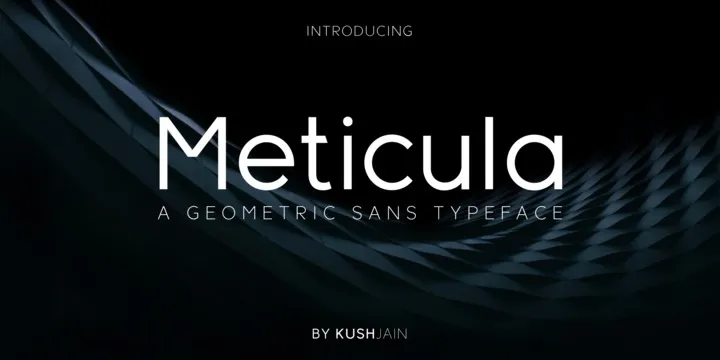
Meticula Font Family
A Meticula Font Family é uma famosa família de fontes sans-serif projetada pela 24Design, que vem com 18 diferentes tipos. Se você busca letras fortes, compostas por uma variedade de ligaturas únicas e estilos distintos, a Meticula é sua escolha perfeita. Uma fonte memorável, fashionável e elegante, essa família de letras atesta o rigoroso trabalho que 24Design investiu em desenvolvê-la com formas geométricas inspiradas em tipos modernos sans-serif. A famosa Meticula vem embalada com 8 versões estilizadas e um font in-line apresentando ganchos acentuados. Além disso, a família inclui uma tipografia itálica que complementa as formas rectângulares de sua versão estándar. Nossa introdução à Meticula é perfeita para quem valoriza elegância na tipografia e deseja incorporar um toque moderno em projetos. Com suas formas geométricas cuidadosamente construídas, a Meticula atinge uma mistura arrojada de clássico e inovador, tornando-a uma fonte perfeita para qualquer aplicação visual que busque ser contemporânea e memorável.